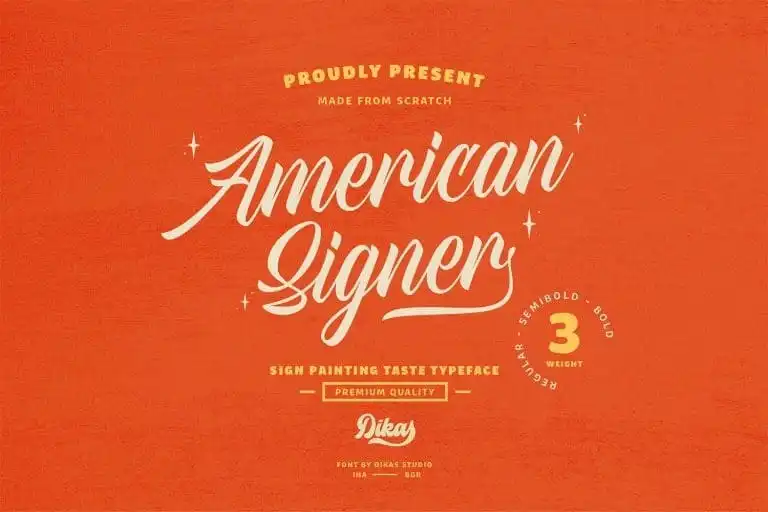
American Signer Script Font – Download Grátis
Descubra a elegância moderna do American Signer Script Font – uma tipografia script que inspirou-se nos traços fortes das pinturas de sinais do início dos anos 80. Este novo lançamento foi meticulosamente digitado diretamente a partir da escrita com pincel, proporcionando um estilo perfeito para resgatar o encanto nostálgico da arte da pintura de sinais. Seja você designer de graphic design, ilustrador ou artista digital, este fonte apresentará uma paleta visual que vai reviver os tempos dos sinalizadores coloridos e criativamente expressivos. Com a capacidade de personalizar e a facilidade de uso, o American Signer Script Font é um recurso valioso para qualquer designer em busca de incorporar a arte da pintura de sinais em suas criações. Não deixe de experimentá-lo – ele certamente vai transformar sua obra de design.